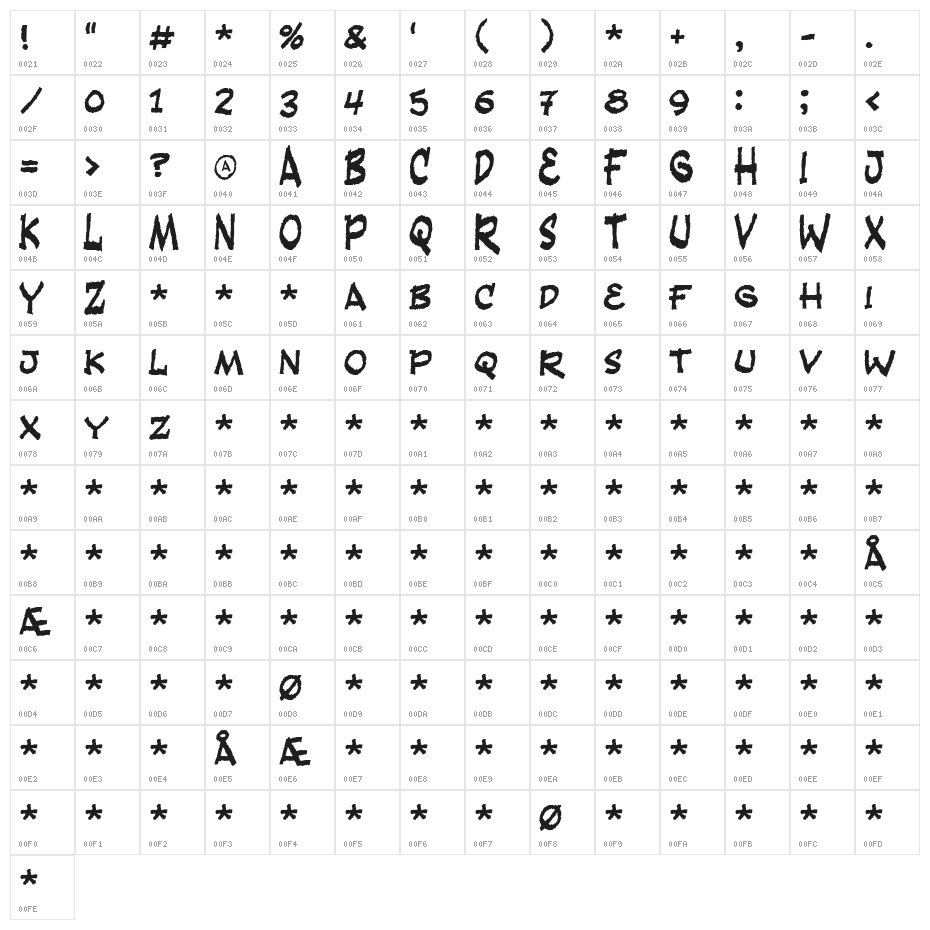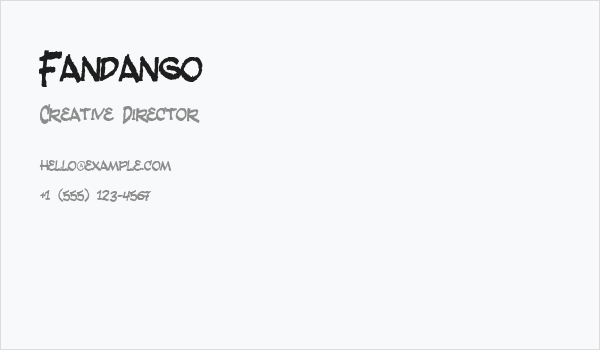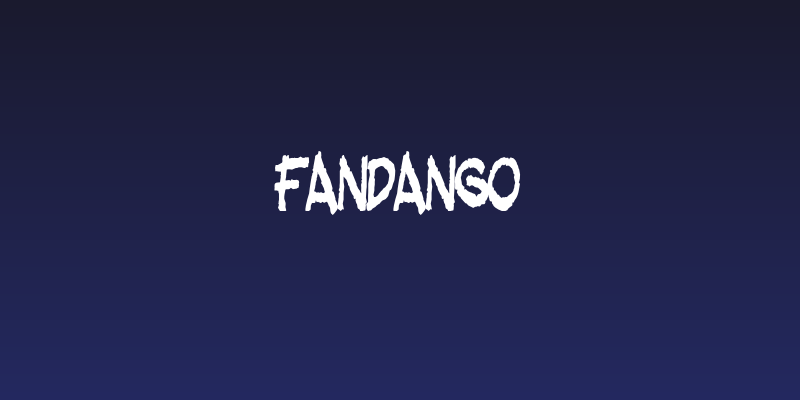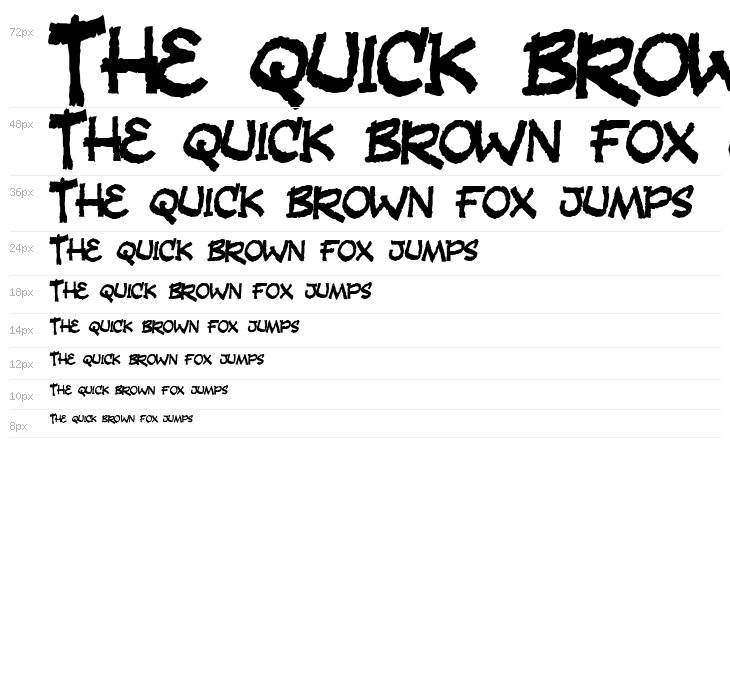
Fandango Font
| Caso d'uso | Logos, Posters, Headlines |
| Progetti proposti | Ideal for street art designs, music album covers, event posters, and edgy branding projects. |